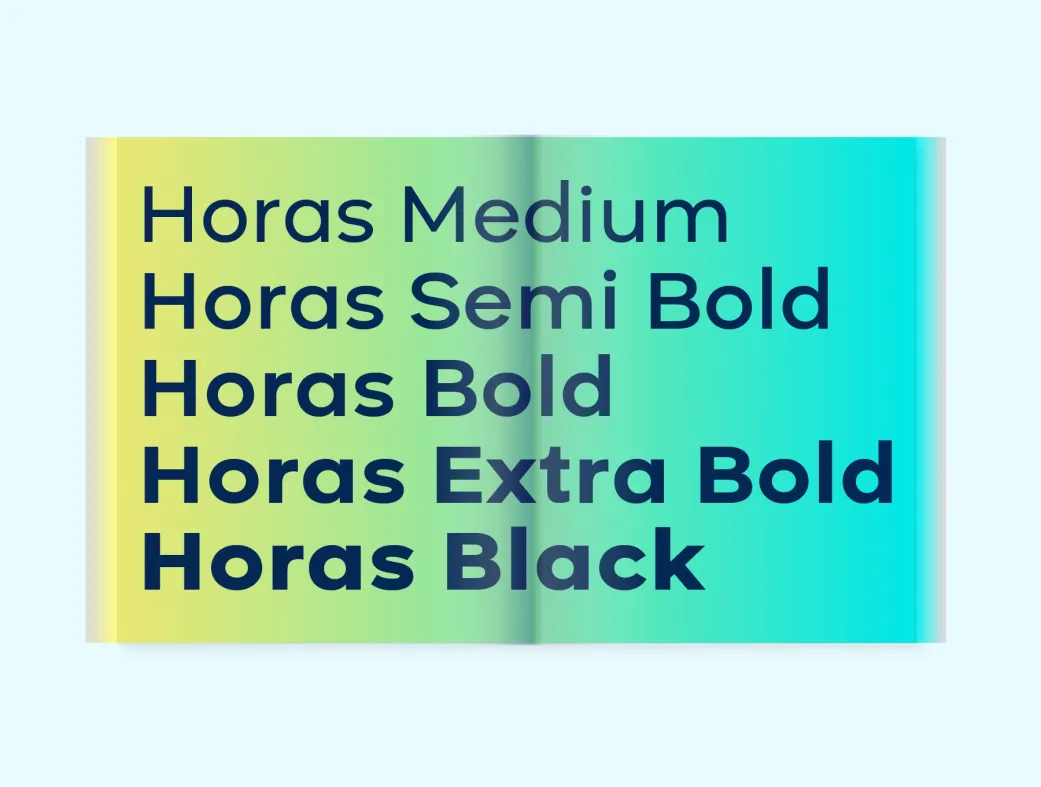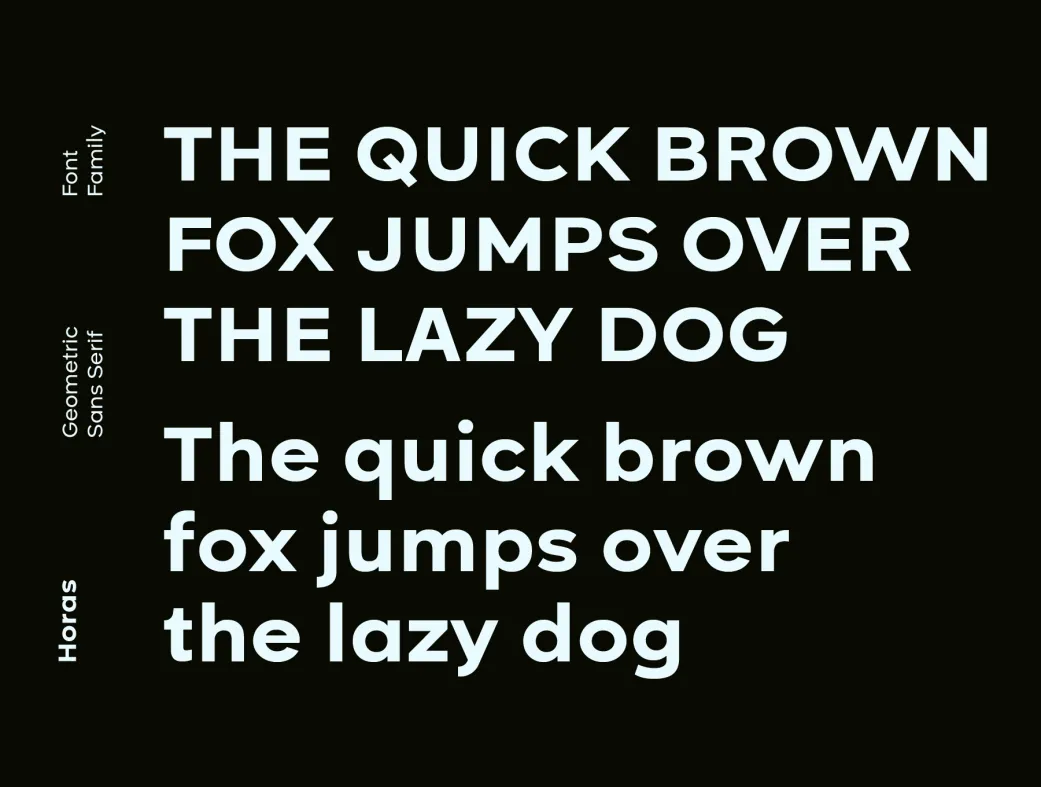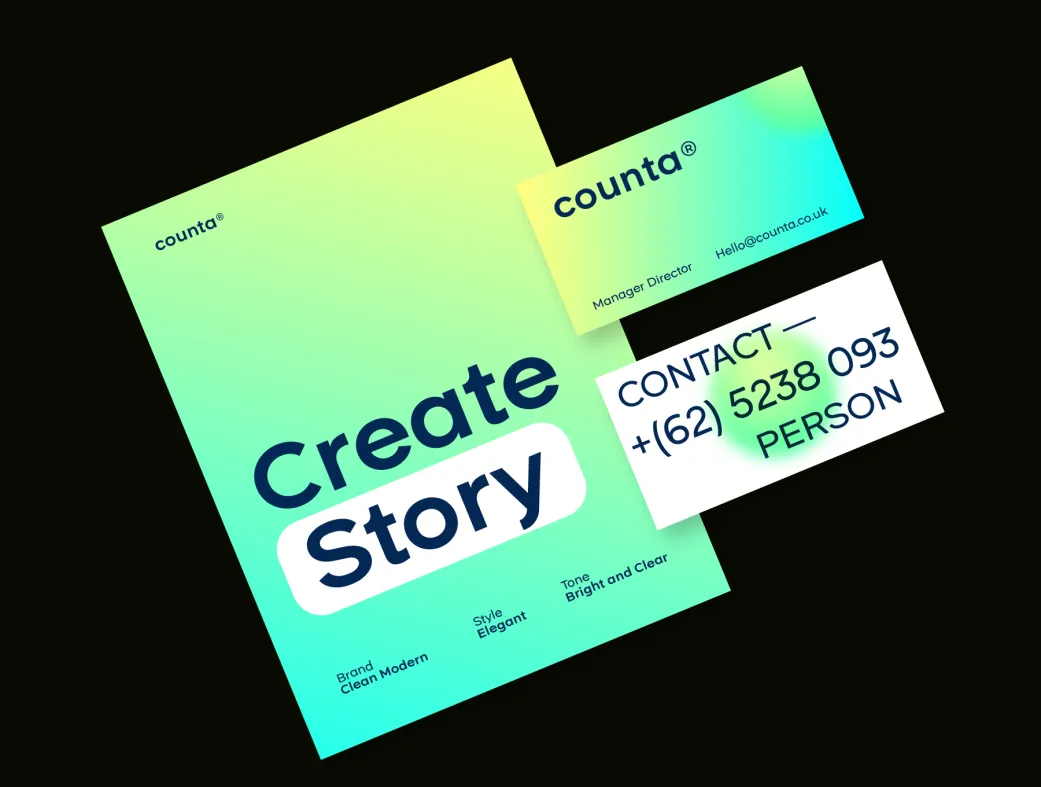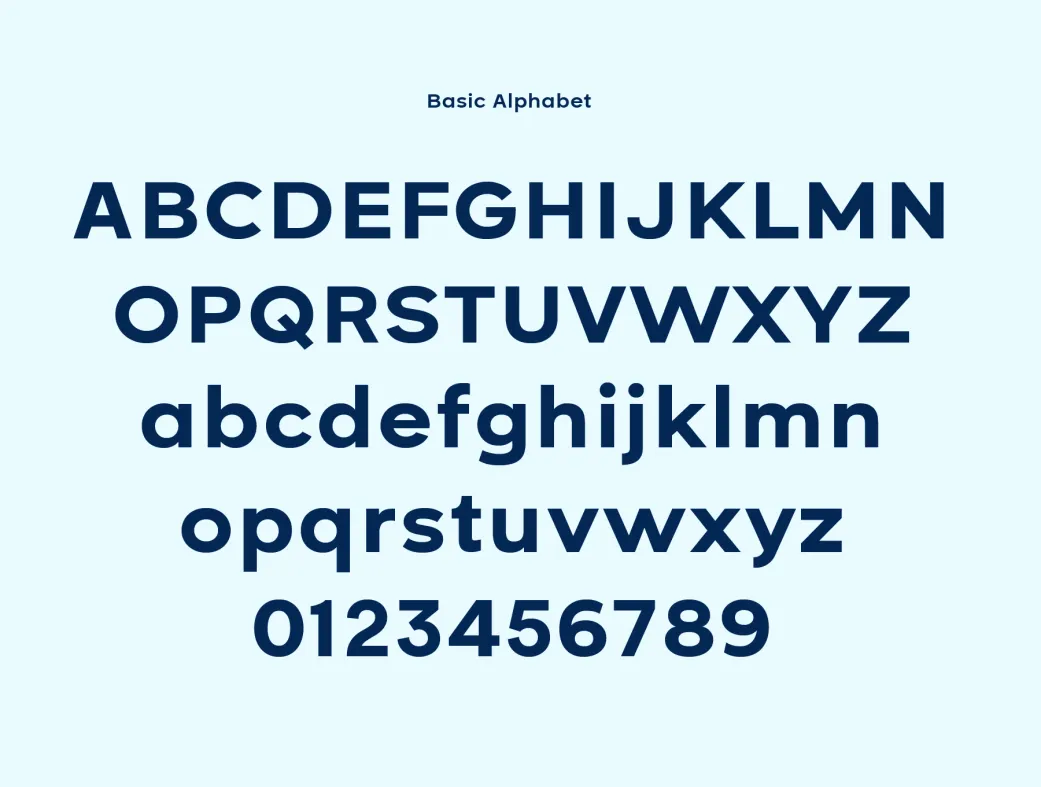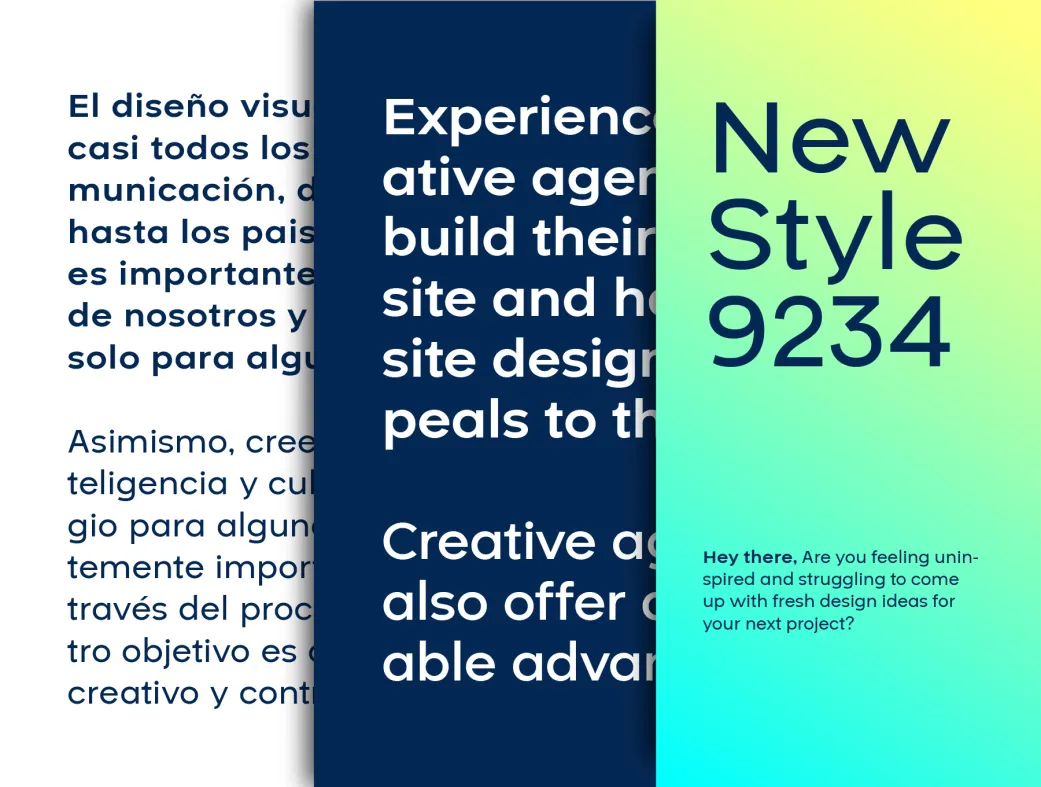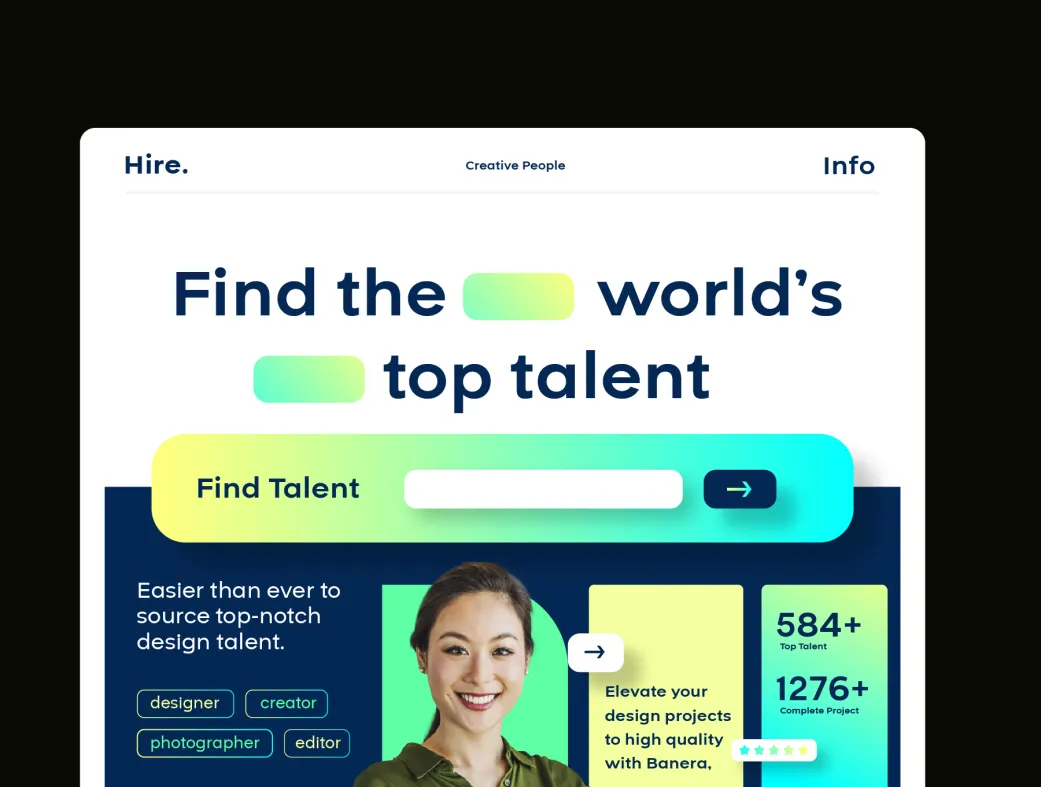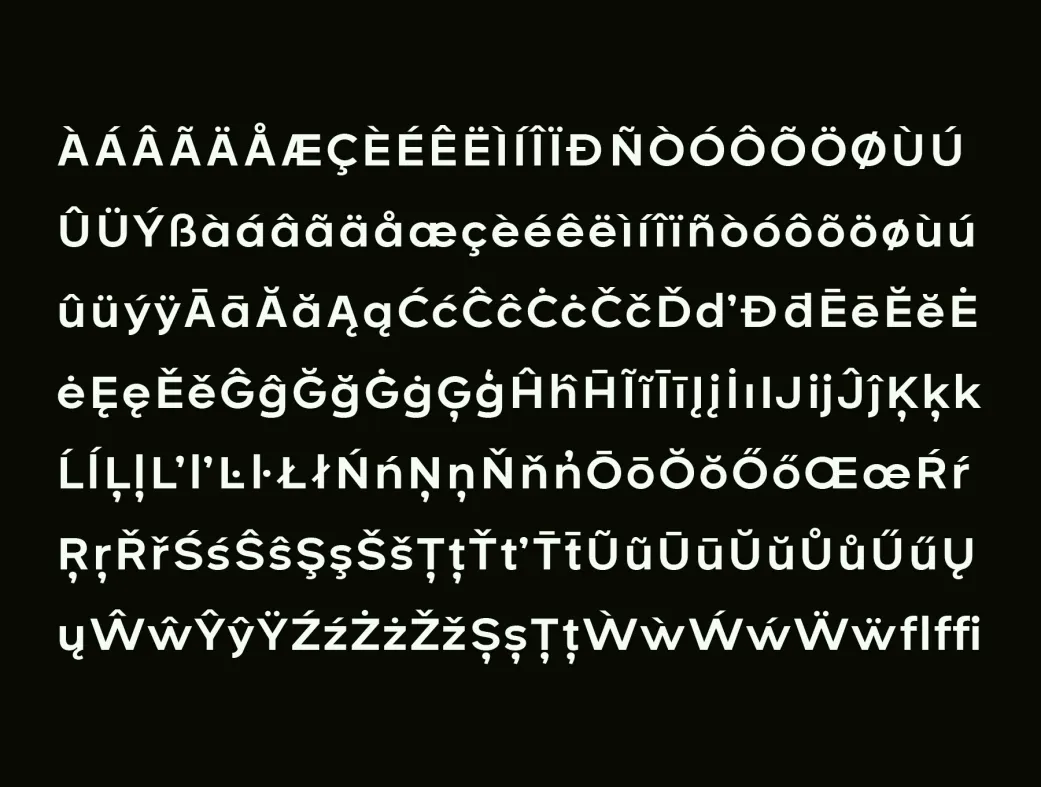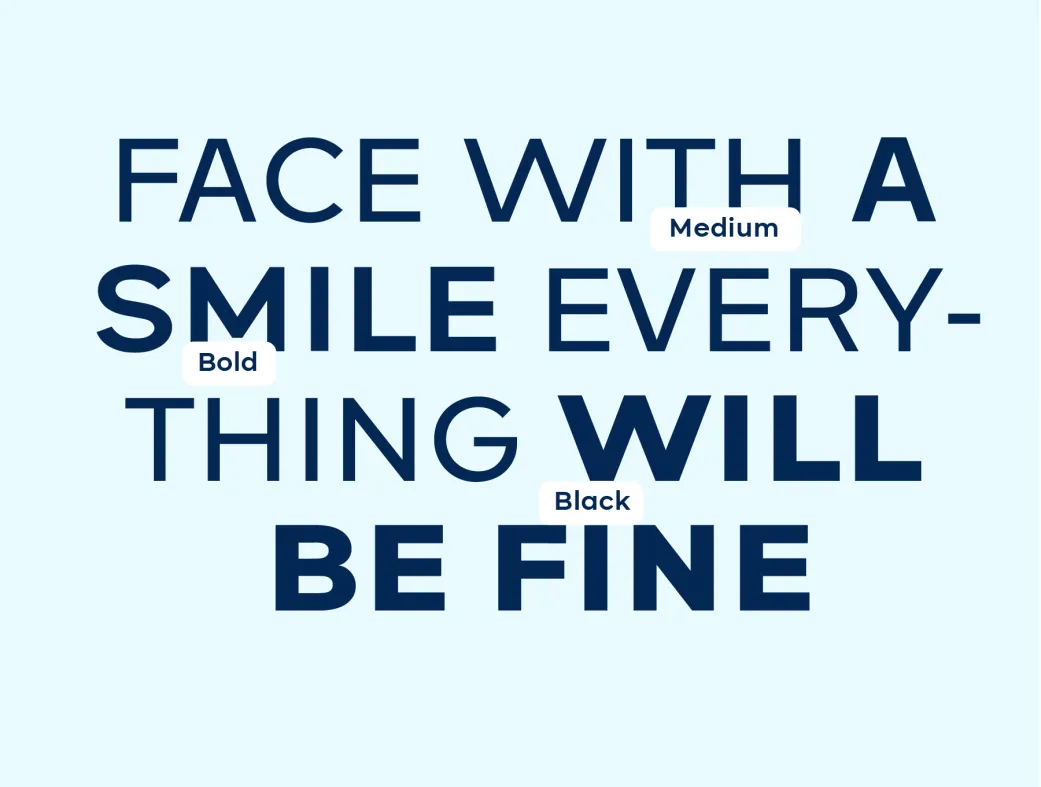
فونت هندسی رایگان هوراس | Horas
آیا به دنبال طراحی مدرن هستید؟ فونت هندسی هوراس، رایگان و مناسب برای هر پروژه!
Horas Geometric Font
فونت هندسی رایگان هوراس | Horas | فونت هندسی هوراس
فونت هندسی هوراس (Horas Sans Serif Geometric) یک فونت مدرن و خیره‌کننده است که با لمسی از مینیمالیسم و هندسه جذاب طراحی شده است. این فونت زیبایی طراحی بدون سریف را با جسارت شکل‌های هندسی ترکیب می‌کند و ظاهری تازه و تمیز برای پروژه‌های طراحی مختلف ایجاد می‌نماید.
فونت هوراس برای استفاده در رسانه‌های مختلف، چه چاپی و چه دیجیتال، مناسب است. در طراحی‌های چاپی، این فونت ظاهری حرفه‌ای و تمیز به پروژه‌های شما می‌بخشد و در طراحی‌های دیجیتال، به وضوح و شفافیت بر روی نمایشگرهای با هر اندازه‌ای جلوه‌گری می‌کند.
علاوه بر این، هندسه جذاب و طراحی بدون سریف آن، این فونت را به گزینه‌ای ایده‌آل برای طراحان و برندها تبدیل کرده است که به دنبال ایجاد هویتی مدرن و متمایز هستند. با استفاده از فونت هوراس، می‌توانید طراحی‌های خود را به سطحی جدید ارتقا دهید و تأثیر بصری قوی‌تری بر روی مخاطبان خود بگذارید.
این فونت برای طراحان حرفه‌ای و مبتدی مناسب است. طراحان می‌توانند از این فونت در طراحی‌های لوگو، پوستر، وب‌سایت‌ها و هر نوع پروژه‌ای که نیاز به ظاهری مدرن و شیک دارد، استفاده کنند. همچنین، استفاده از این فونت در متون دیجیتال و چاپی به خوانایی و جذابیت بیشتر مطالب کمک می‌کند.